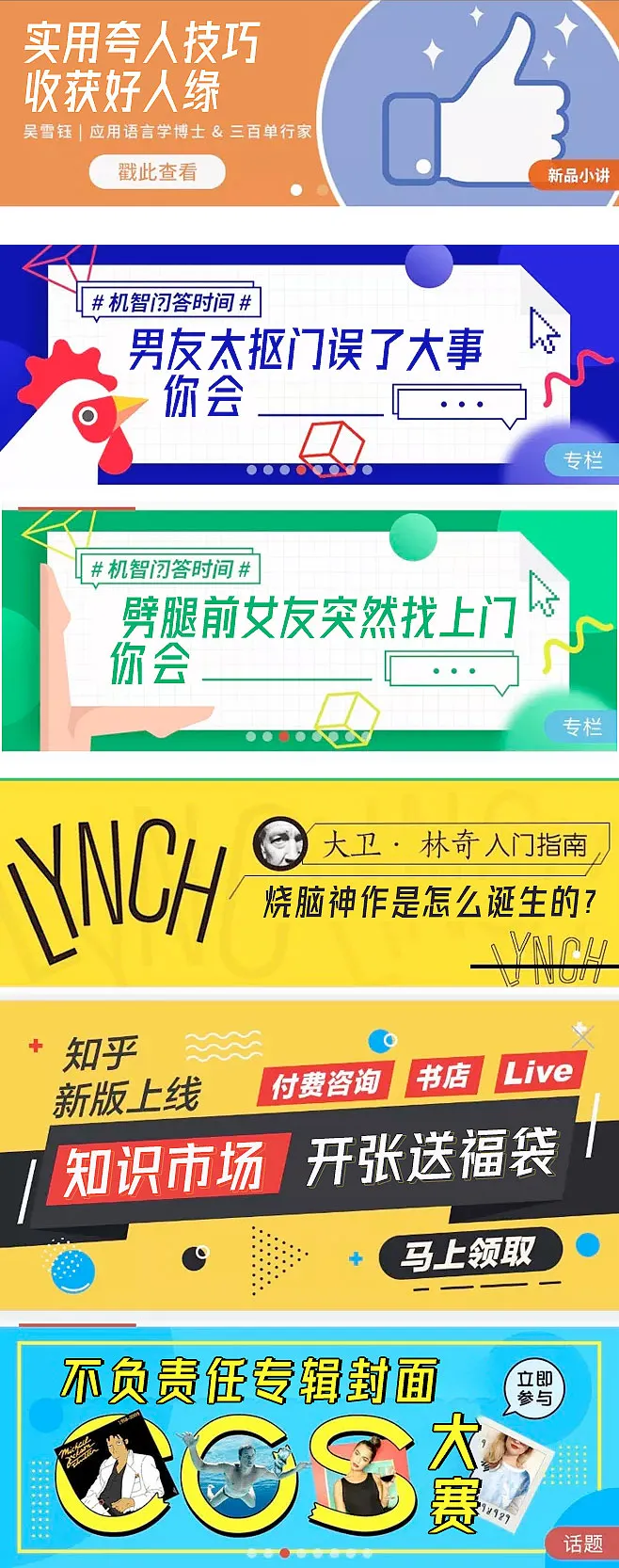
字體圈欣意冠黑體 詳情頁
字體名稱: 字體圈欣意冠黑
字體圈欣意冠黑體
字體圈欣意冠黑體介紹
2020.8月更新3.0版本
1:更改部分字形設計
2:重新設計西文數字標點部分
3:添加3000+個繁體字符,現在字符數量是將近10000個了
4:還原字形默認大小
5:添加了生僻字“biang”
2020.04.21日更新2.0版本
作者:字體設計師鄒樂偉
字體圈欣意冠黑體字體欣意冠黑體字庫是一款讓人賞心悅目、百看不厭的中文字體,適合各類廣告和產品包裝設計應用,字體大小2.03MB,格式為ttf字體,上傳用戶是神經蛙6,作者/版權方為字體圈/鄒樂偉